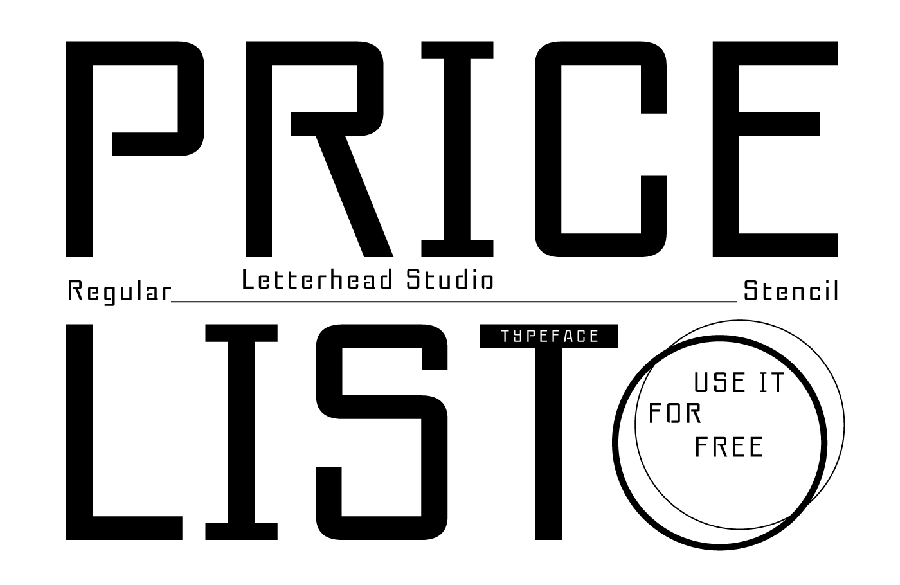
Descubra a Pricelist™ Typeface, uma nova família de linhas gêmeas inspirada nas especificações mecânicas. Especialmente projetada para os designers que valorizam elementos geométricos e simplicidade, esta fonte é perfeita para uma variedade de aplicativos de design. Inspirada no formato padrão dos listagens de preços, ela se destaca como um tipo de exibição perfeito para anúncios e revistas. A Pricelist™ Typeface não apenas reforça a consistência visual em suas campanhas publicitárias, mas também adiciona uma personalidade única à sua identidade visual. Com seu design minimalista e geométrico, ela se tornará um recurso indispensável para qualquer projeto que exige uma aparência limpa e moderna.